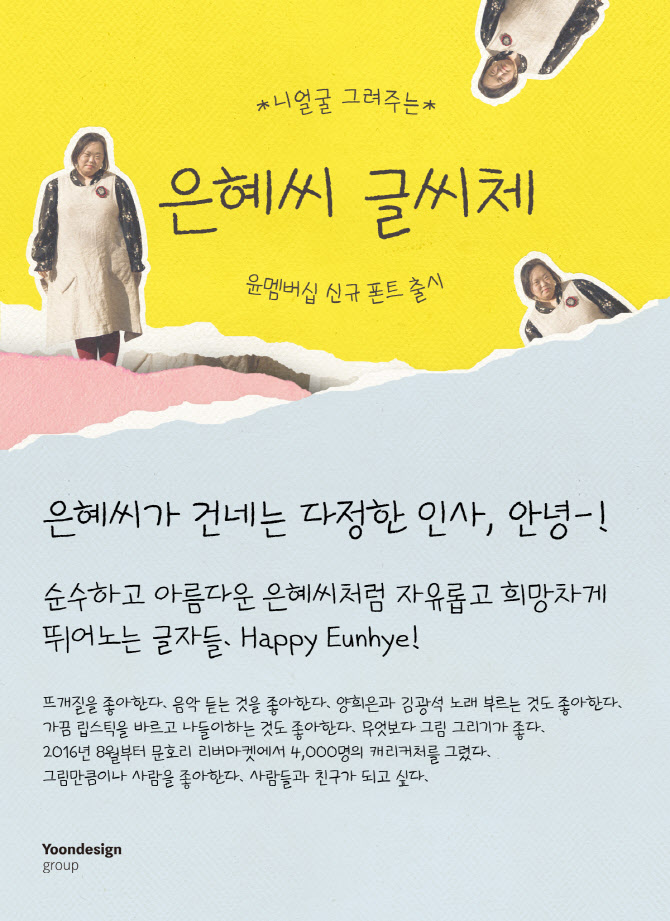
윤디자인그룹, 정은혜 작가의 손글씨 폰트 ‘은혜씨 글씨체’ 개발
- - 안성탕면체, 벨리곰체, 교보 손글씨 등 개발해온 윤디자인그룹, 이번엔 정은혜 작가와 협업
- - 작가가 직접 쓴 손글씨 원도를 바탕으로 윤디자인그룹이 폰트 개발
㈜윤디자인그룹(회장 편석훈)이 미술 작가이자 드라마 <우리들의 블루스> 등 배우로도 활동하고 있는 정은혜 작가의 손글씨를 디지털 폰트로 개발했다.
정은혜 작가가 직접 쓴 손글씨 원도를 바탕으로 개발한 ‘은혜씨 글씨체’ 폰트는 순수하고 아름다운 작가의 작품처럼 자유롭고 희망차게 글자들이 뛰어노는 듯한 느낌이 특징이다. 작가가 자주 사용하는 연필의 질감을 표현해 생동감이 느껴지며, 글자 형태와 크기를 다양하게 제작하여 작가만의 자유로운 필체를 그대로 반영했다.
정은혜 작가는 2016년부터 4,000명이 넘는 사람들의 캐리커처를 그려왔으며, 그림집 <니얼굴>과 <은혜씨의 포옹>, 다수의 개인전과 초대전 등 활발하게 창작활동을 이어오고 있다. 또한 드라마 <우리들의 블루스>에서 배우 한지민의 쌍둥이 언니 ‘영희’ 역을 맡아 연기했으며, 다큐멘터리 영화 <니얼굴>의 주인공으로 출연하였다. 다양한 창작 활동으로 희망과 감동을 선사해온 정은혜 작가는 이번 손글씨 폰트 개발을 통해 대중에게 더욱더 친근하게 다가가고자 한다.